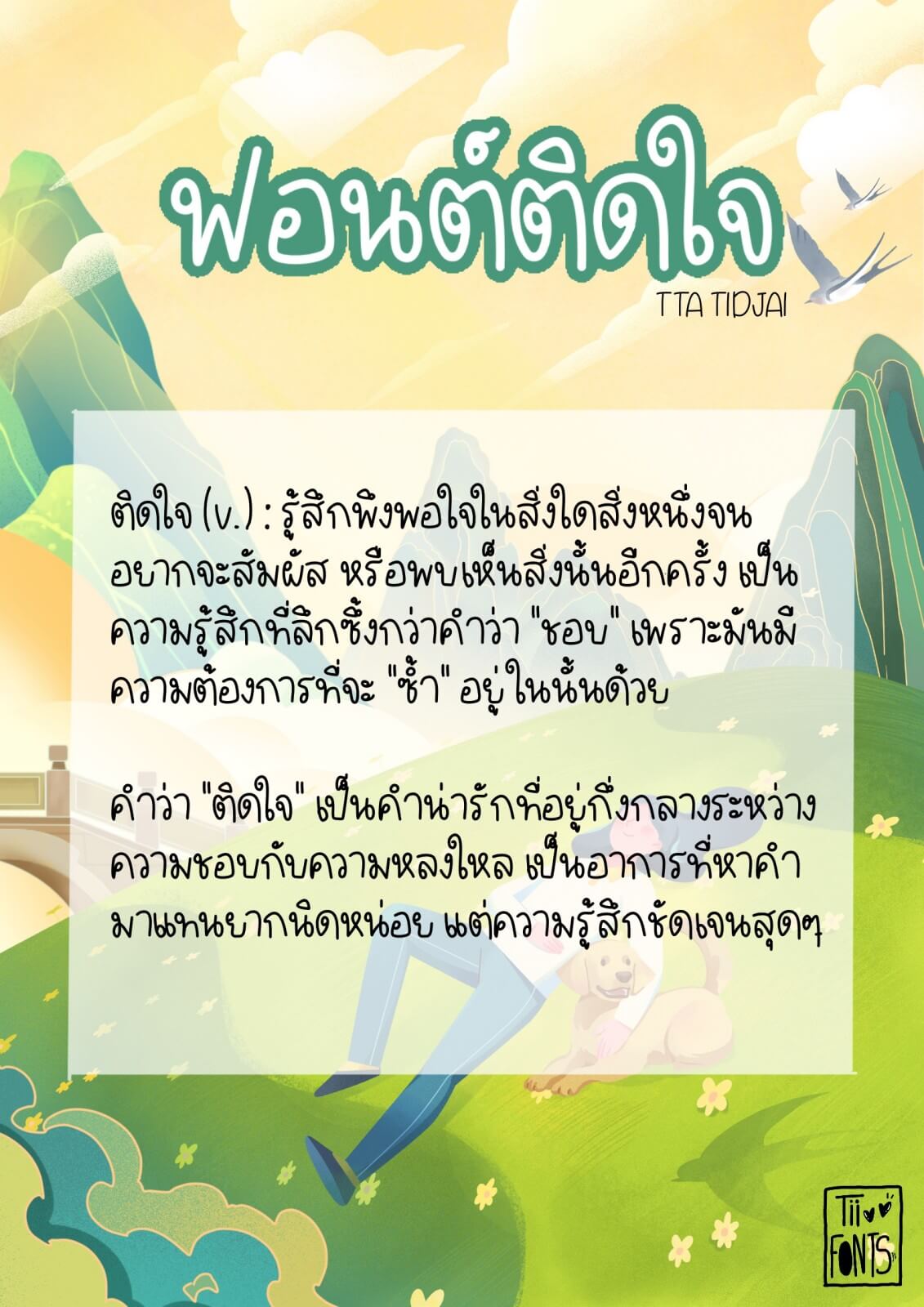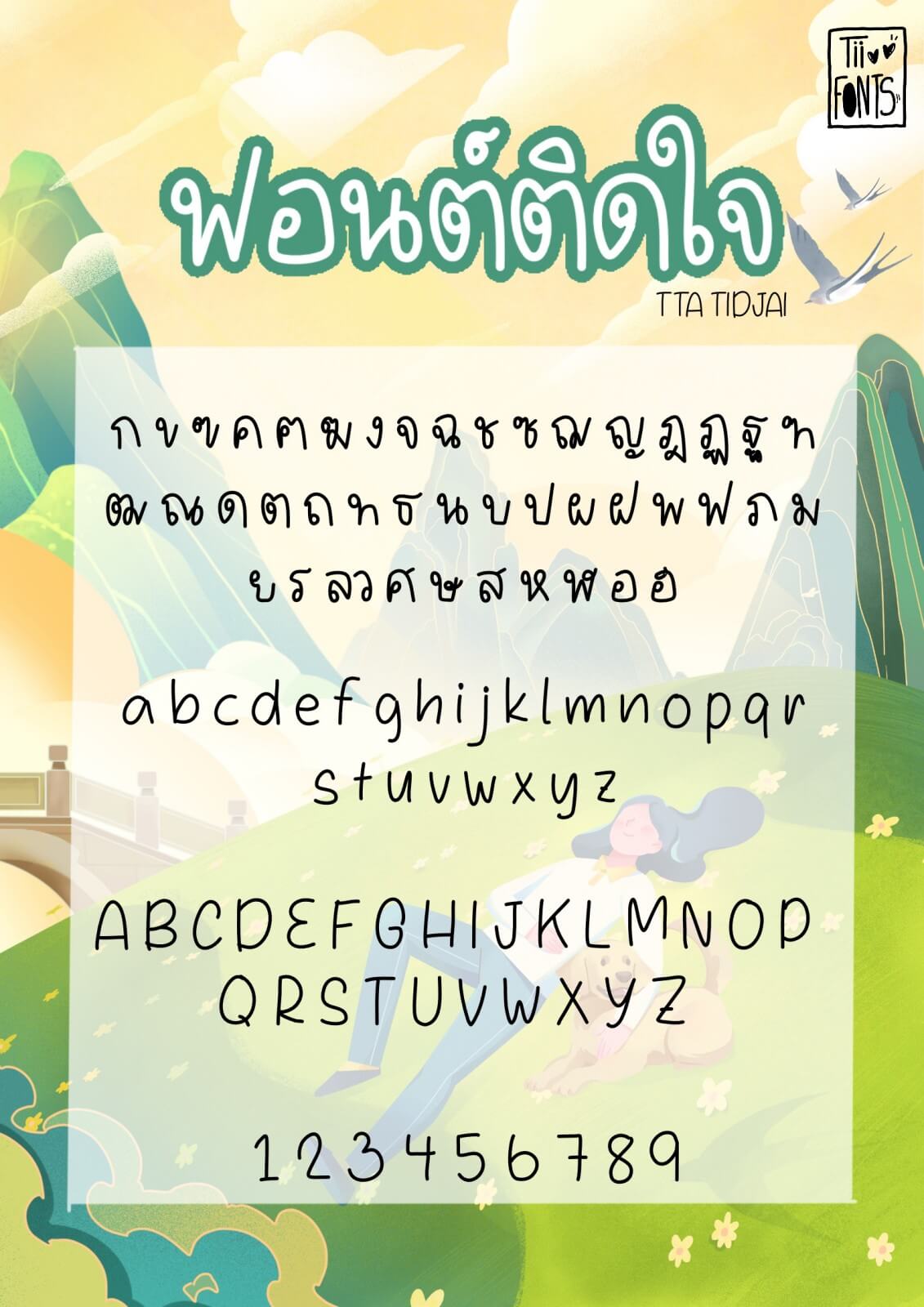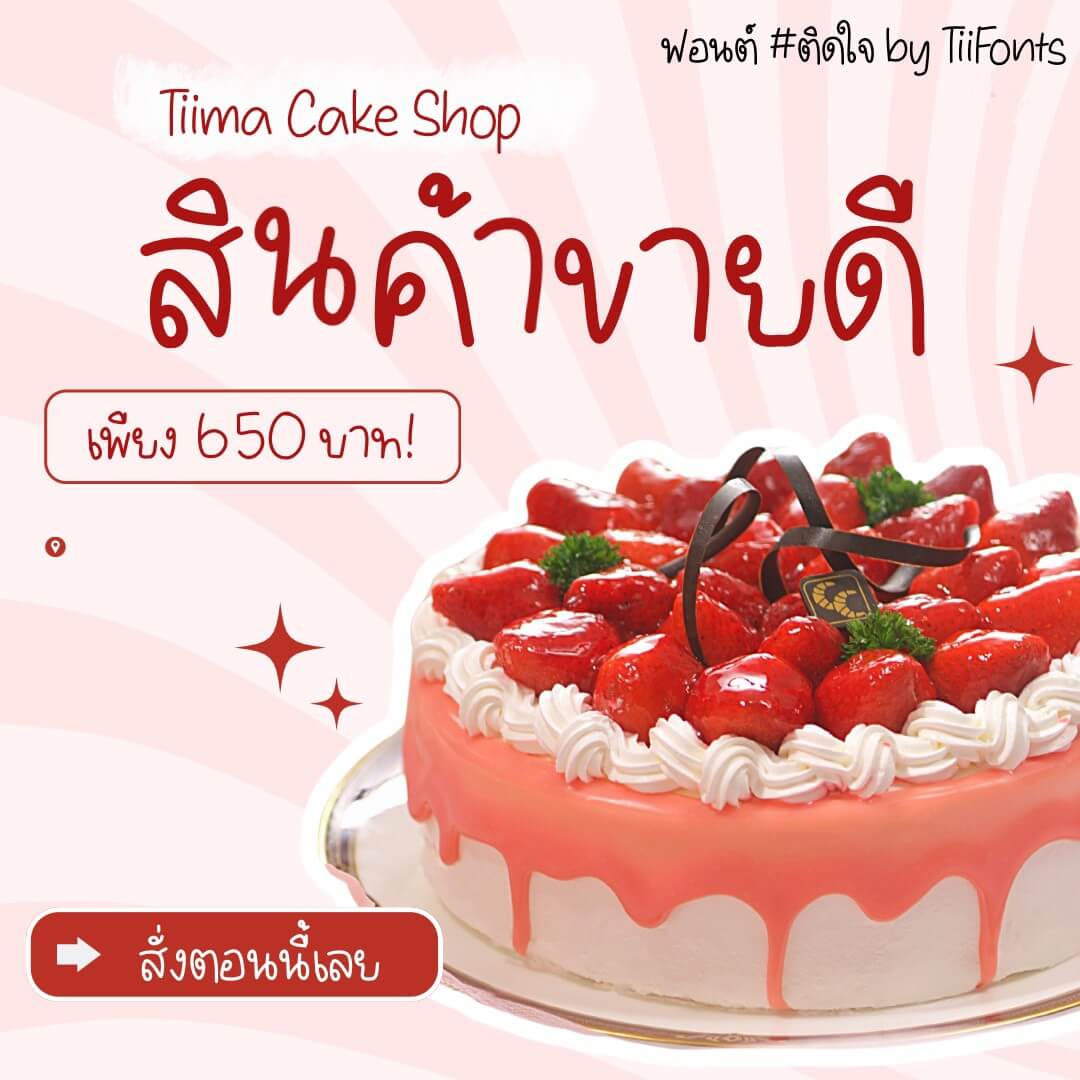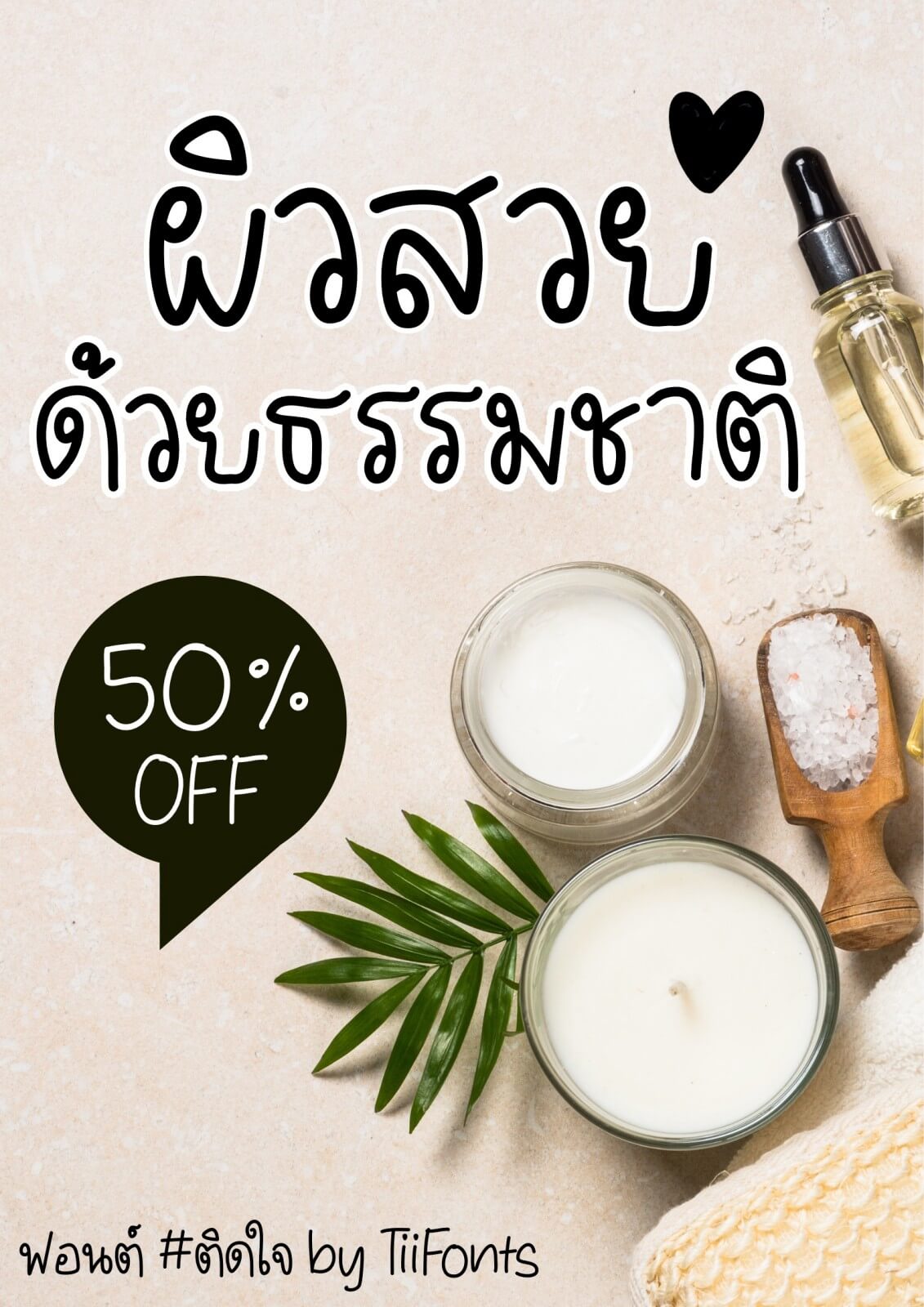
ฟอนต์นี้ถูกออกแบบมาให้อยู่กึ่งกลางระหว่างความน่ารักและความเป็นกันเอง ซนๆ อ่านง่ายแต่ยังมีเอกลักษณ์เฉพาะตัว จะเอาไปแต่งรูปคาเฟ่ ทำสรุปเรียน ใช้ในงานโปรโมตสินค้า หรือ Presentation ก็เพิ่มความซอฟต์ให้งานดูละมุนออกแนวน่ารักซนๆ ขึ้น 100%